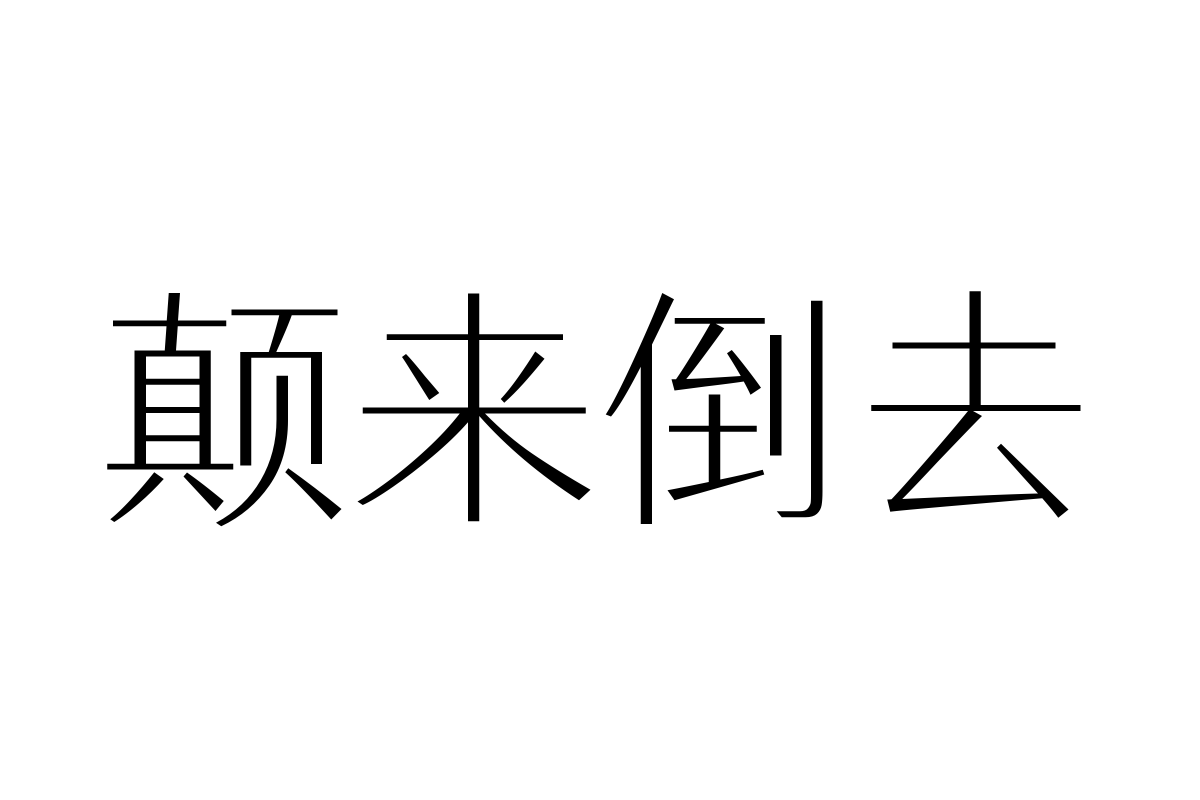
汉林细体是一款具有现代感的中文字体,其特点是字形纤细、清晰。这款字体适用于各种需要展示精细、清晰文字的场合,如广告、报纸、杂志等。汉林细体的特点在于其字形的纤细和清晰度,使得文字看起来更加简洁明了,易于阅读。同时,它的设计也充分考虑了易读性和美观性,使得文字在视觉上呈现出一种平衡和和谐的感觉。总的来说,汉林细体是一款非常适合用于印刷和数字媒体的字体。